好立克發源自英國,是於香港茶餐廳十分常見的麥芽沖劑熱飲品牌。由於其營養豐富,很適合兒童飲用。品牌的商標設計未能突顯其品牌特色,故選了它來作為商標重塑計劃的一次實驗,令其能在眾多新品牌之中突出自己。
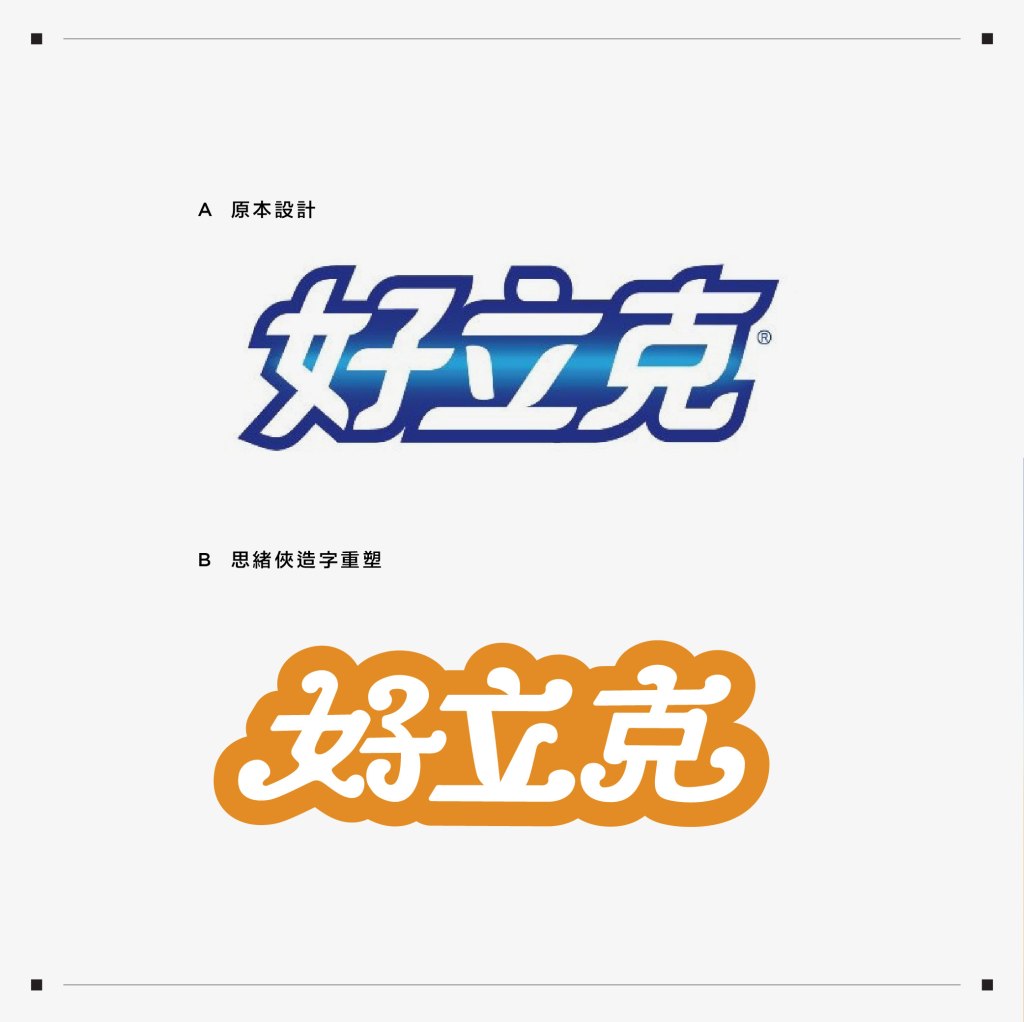
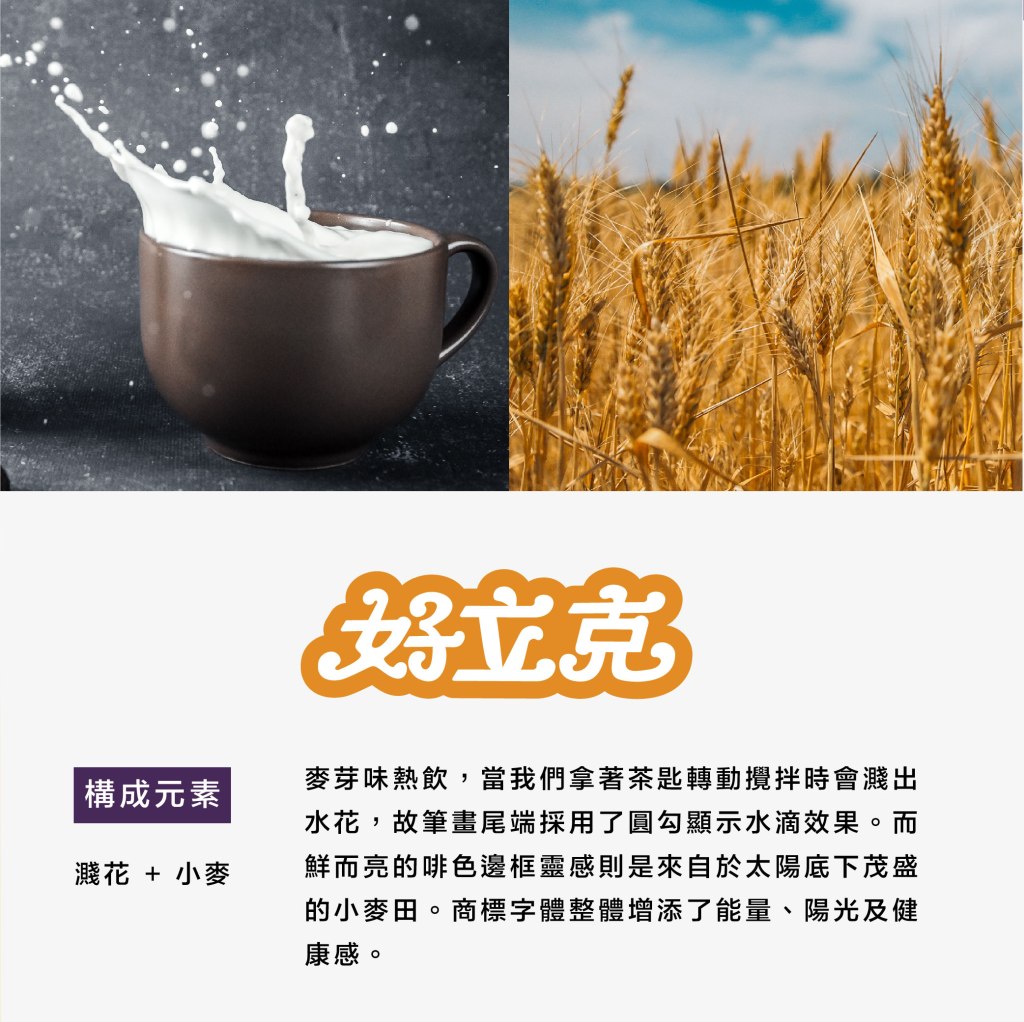
構成元素 【濺花 + 小麥】
麥芽味熱飲,當我們拿著茶匙轉動攪拌時會濺出水花,故筆畫尾端採用了圓勾顯示水滴效果。而鮮而亮的啡色邊框靈感則是來自於太陽底下茂盛的小麥田。商標字體整體增添了能量、陽光及健康感。
好立克發源自英國,是於香港茶餐廳十分常見的麥芽沖劑熱飲品牌。由於其營養豐富,很適合兒童飲用。品牌的商標設計未能突顯其品牌特色,故選了它來作為商標重塑計劃的一次實驗,令其能在眾多新品牌之中突出自己。
構成元素 【濺花 + 小麥】
麥芽味熱飲,當我們拿著茶匙轉動攪拌時會濺出水花,故筆畫尾端採用了圓勾顯示水滴效果。而鮮而亮的啡色邊框靈感則是來自於太陽底下茂盛的小麥田。商標字體整體增添了能量、陽光及健康感。